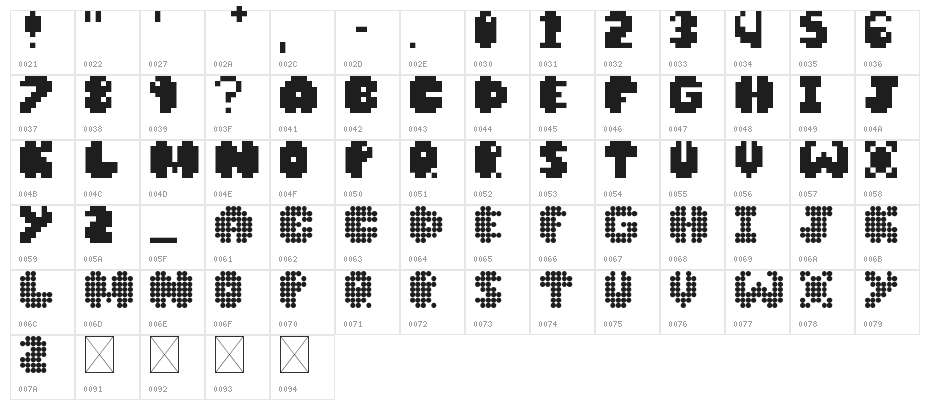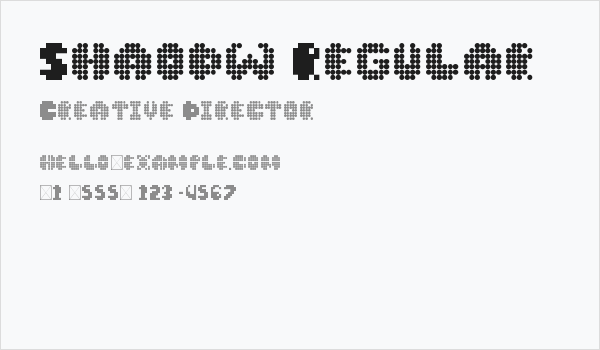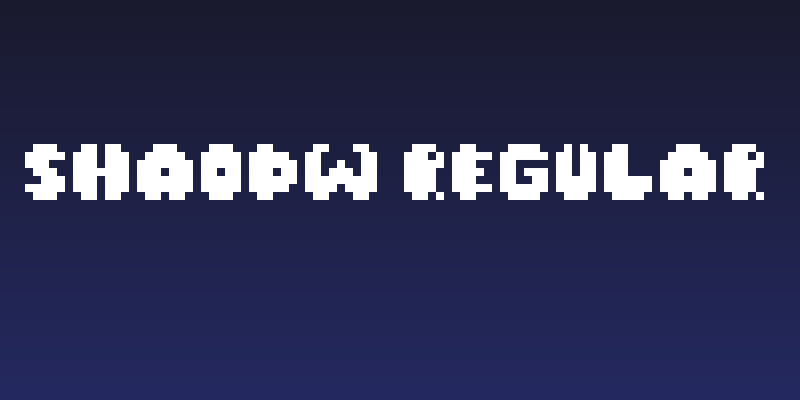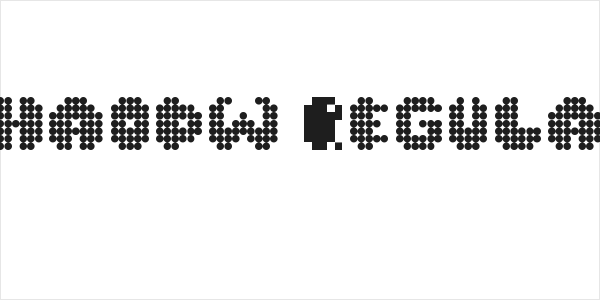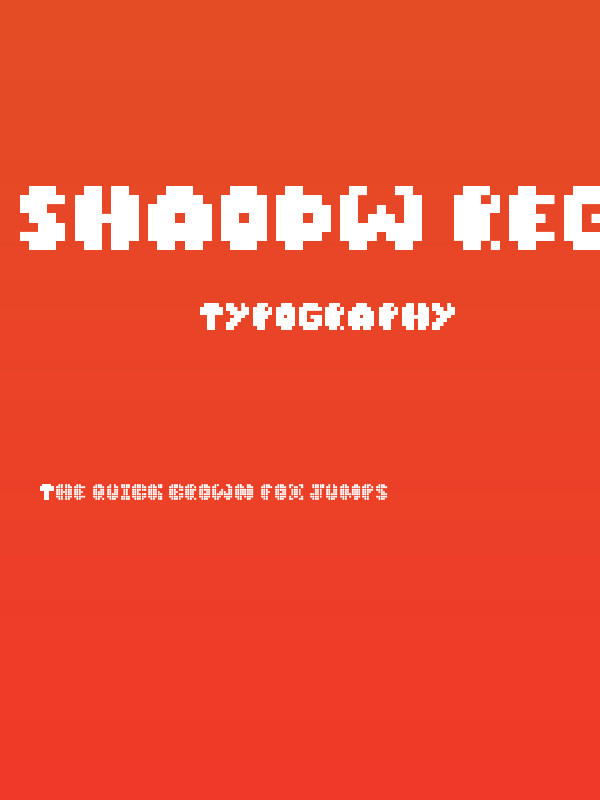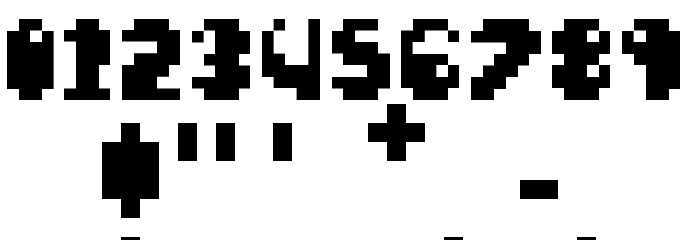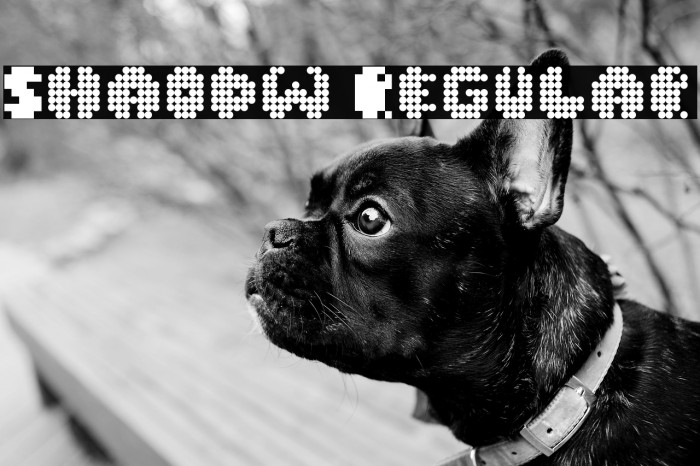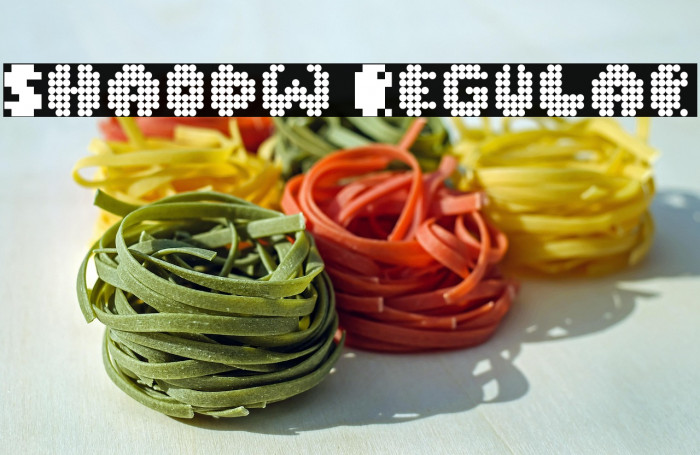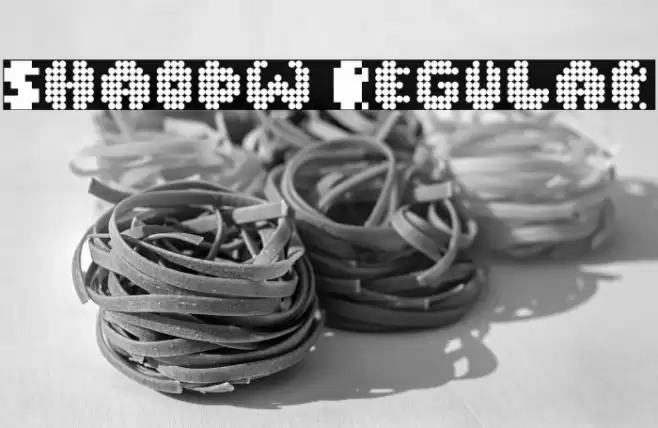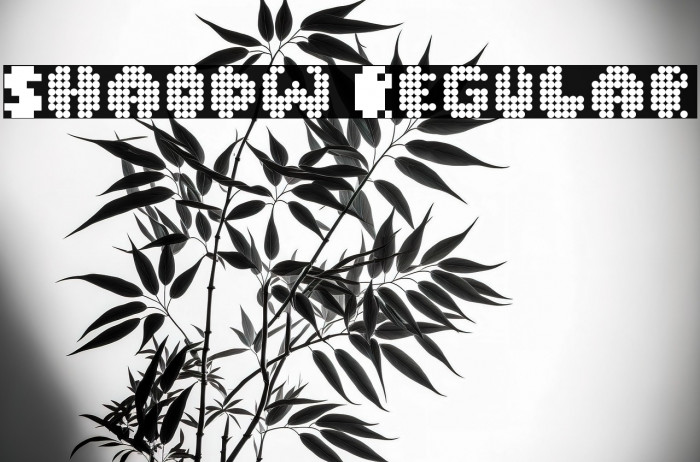
Shaodw Regular Font
✎ Pixel
Fonts by ShadowOnTheLoose
| Categorii | Pixel |
| Stil general | Retro, Digital |
| Proiecte propuse | Ideal for video game graphics, retro-themed posters, digital art projects, and any design that seeks to capture a vintage digital aesthetic. |